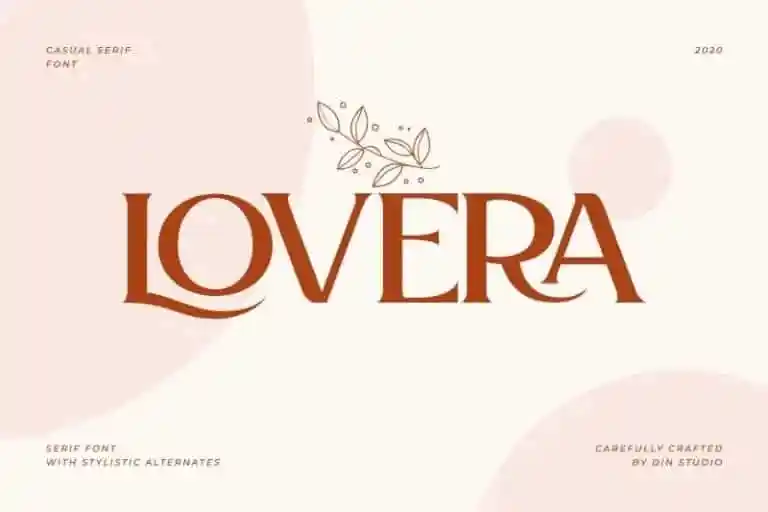
Lovera Serif Font – Fonte Grátis
Lovera Serif Font – Download Grátis
Lovera Serif Font
A fonte “Lovera Serif Font” é inspirada no design elegante dos títulos de livros infantis ou capas de animações. A Din Studio criou e compartilhou essa tipografia, que se destaca por sua sutileza e sofisticação. Seus traços leves e delicados tornam a “Lovera Serif Font” perfeita para qualquer projeto de marca profissional, seja uma campanha publicitária ou um design impresso. Ela é particularmente adequada para aplicações como marcas, cartões de aniversário, e até mesmo frases dedicadas em casamentos. A fonte oferece um toque único em cada letra, tornando-a perfeita para criar designs únicos e memoráveis. Não importa o tipo de projeto ou aplicação que você está trabalhando, “Lovera Serif Font” é uma escolha inteligente que vai deixar seu trabalho destaca-se.